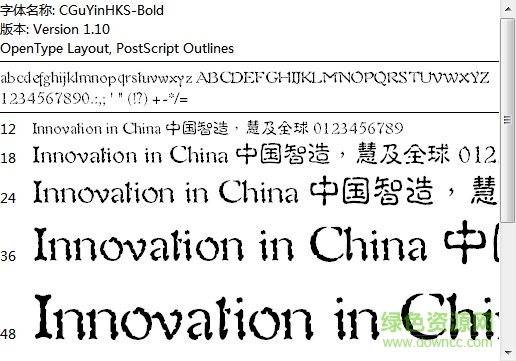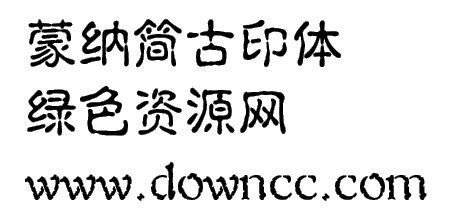
cguyinhks bold蒙納簡古印體
cguyinhks bold即蒙納簡古印體,字跡幾乎古代印刷臨摹的風(fēng)格,造型上的微小間斷,讓文字明滅可見,效果極佳,綠色資源網(wǎng)誠意推薦!
簡古印體特色
簡古印體基于古印字體而設(shè)計(jì),對其進(jìn)行了特殊處理,字形更加美觀大方,整體效果更加出色,可應(yīng)用于雜志報(bào)刊、文學(xué)創(chuàng)作、平面廣告、印刷包裝等領(lǐng)域!